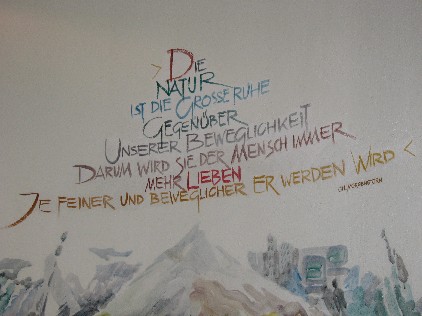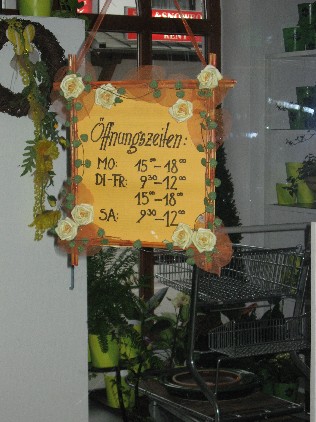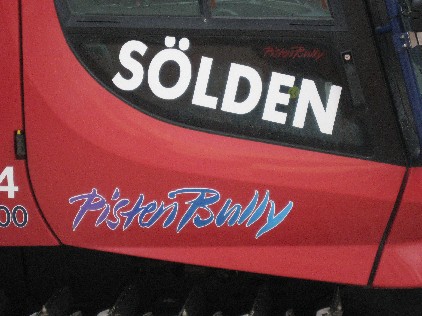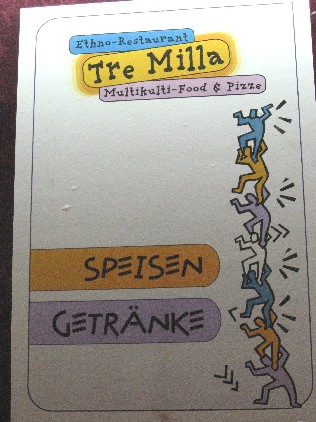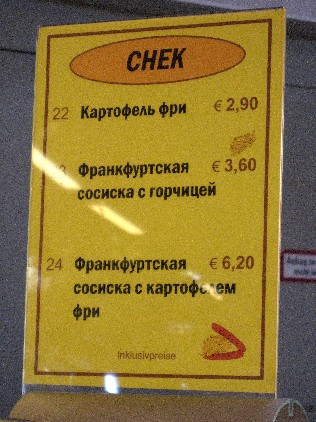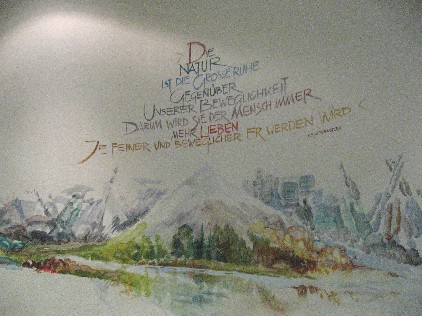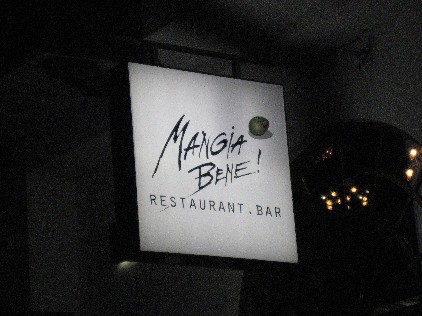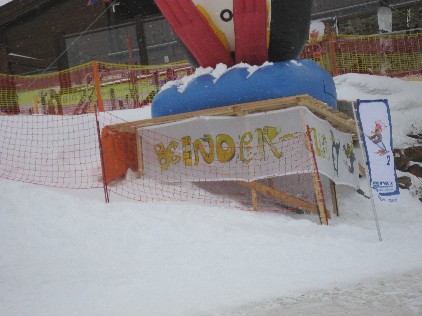
いろんなモジ、文字
今日は、チロルのスキー場を中心に見かけたいろんなモジさんをご紹介します。
やはりカリ人なので、そこここにあるアルファベットに目がいって
しまいますねぇ…。
今回は手書き風、もしくは手書き?かわいいデザインのものを
撮影してみました。
スキー場ではお世話になる雪上車!真っ赤なボディにスカイブルーが爽やか!筆で書いた
っぽいモジが軽快さを感じさせますね。しかもキリリッとしていてカッコいい!
町に架かっていたレストランの看板も筆っぽいですね。
この手書き風がおしゃれに見えて、ちょっと都会風ですか?
スキー場に設けられている子供用のエリアにはこんな可愛いモジが!
スキー用品とか子供の好きなものとかでデザインしてありますねぇ〜。これすごく気に入りました!スキー帽とかスキー板とか本当にラブリー〜!カードとかに応用できそうです。
お花屋さんの看板!ドイツ語圏ではこのような手書モジで書かれた
看板をよく見かけます。
手書きのモジも似てますね…。
ちょっと丸っこくて…。とても可愛いです。
お店の壁に書かれているのは完全に手書きでした!絵もモジも同じ人が描いたのでしょうねぇ〜。水彩で書いたのかしら?壁に?色使いが淡くて優しい感じです。詩の内容は訳すのが難しいですが…自然のことを書いているのでその詩に合っていますね。
人間の慌しさに比べて自然の雄大さを讃えてるって感じかしら〜?
レストランの看板にも可愛いモジが…普通の活字を使うより
楽しい感じですね!
これはおまけ1!
もちろんタイトルのモジが可愛いですが、何と山頂レストランでお寿司が食べられるとは!!!
これもおまけ2!
おやおや?変ったモジですねぇ〜!
…何しろスキー場や町では至る所で「ロシア語」が飛び交って